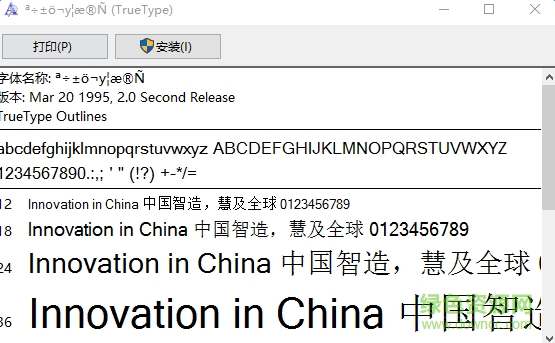
金梅流行書
金梅流行書字體是一款很工整規(guī)范的電腦簡體字體,這種字體一般都是很實(shí)用的,用到的范圍也比較廣,小編已經(jīng)將這款字體打包好了,大家如果喜歡這款字體的話可以隨時來綠色資源網(wǎng)下載使用。
金梅流行書字體是金梅字庫中實(shí)用性很強(qiáng)的字體,而且寫出來的字是很好看的,大方、整齊,給人一種很穩(wěn)重的感覺,歡迎有需要的朋友來綠色資源網(wǎng)下載。